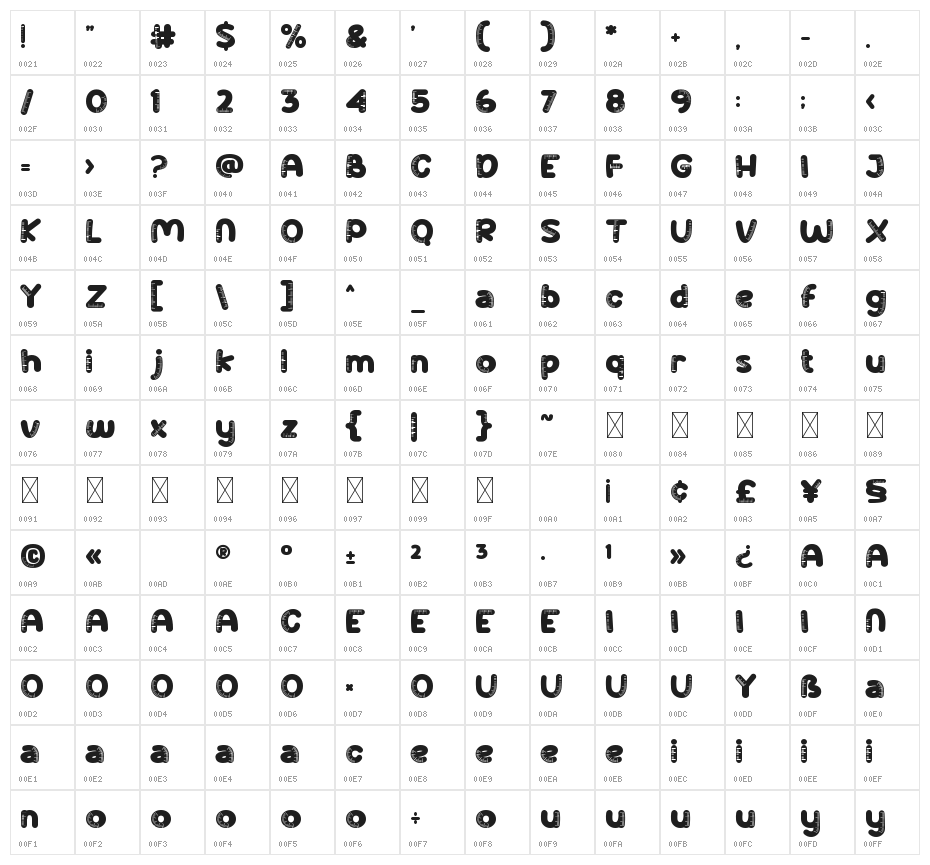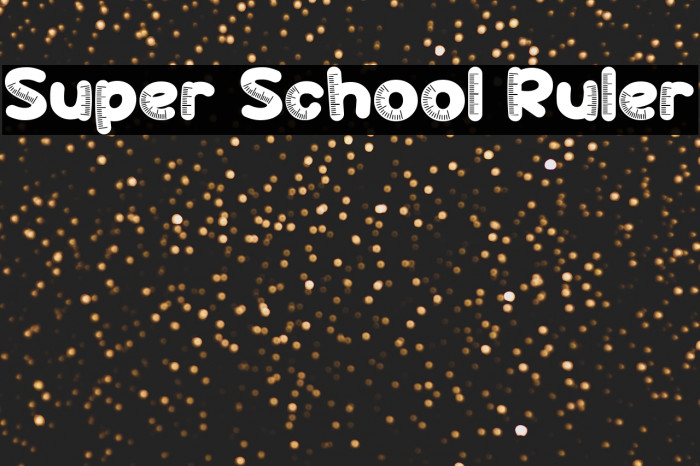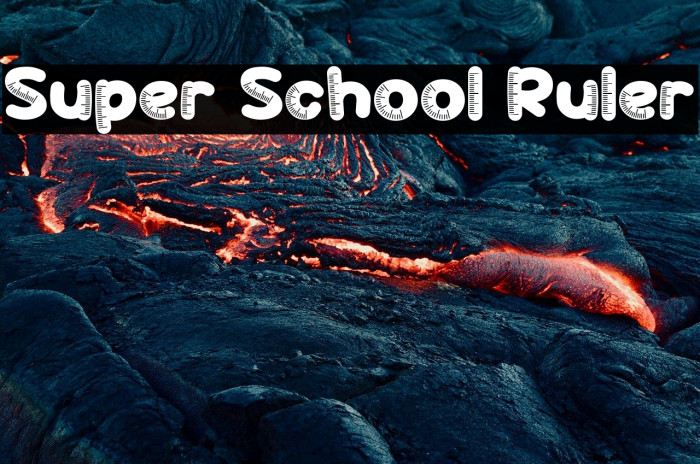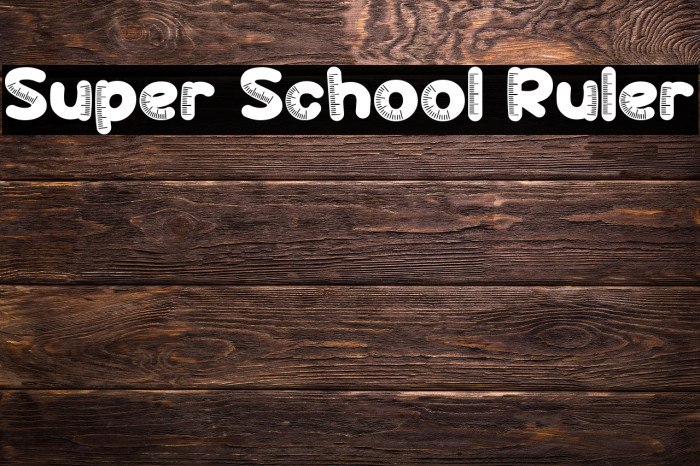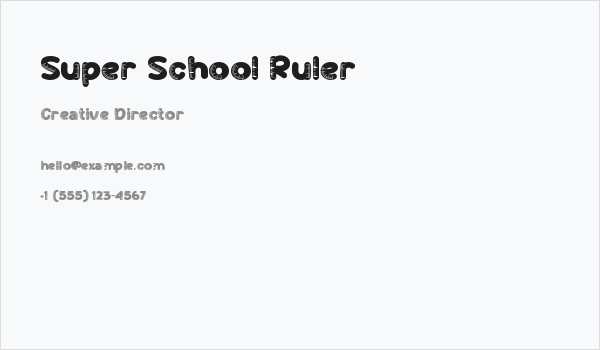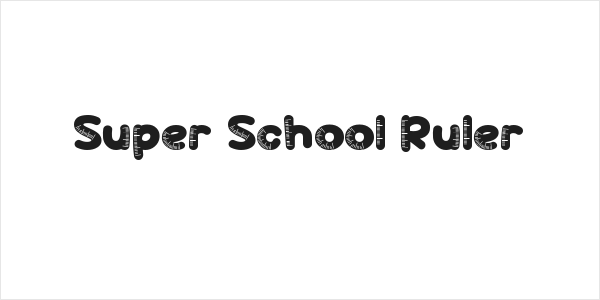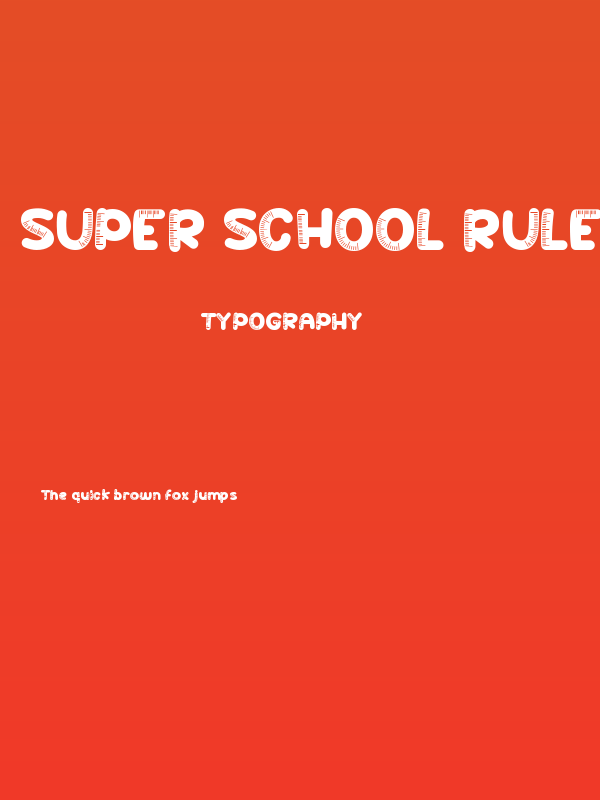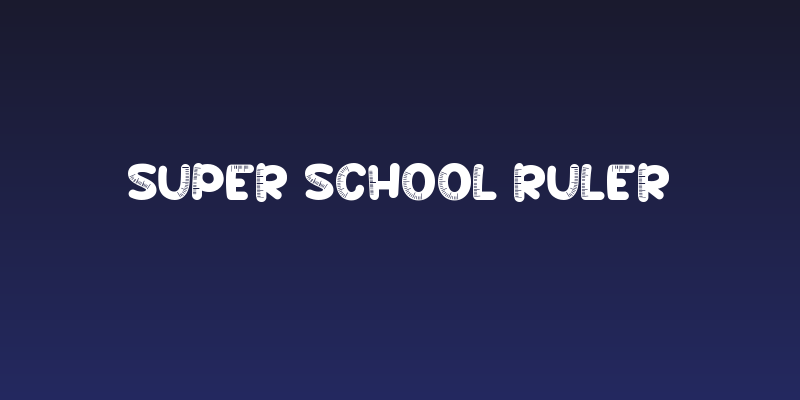
Super School Ruler Font
| Stile generale | Playful, Educational |
| Caso d'uso | Headlines, Posters, Educational Materials |
| Progetti proposti | Ideal for educational materials, children's books, school posters, and playful branding. |